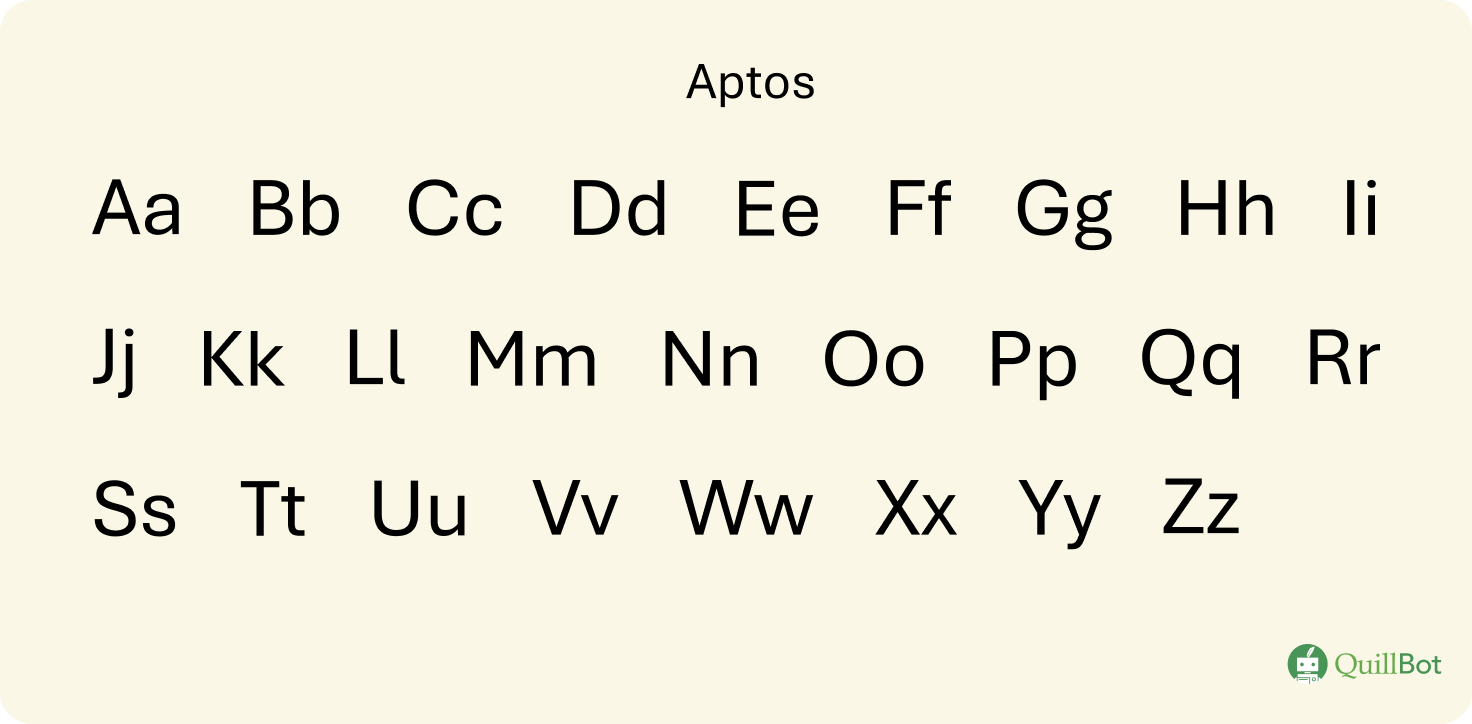
Aptos | La nouvelle police qui monte
Avril 2021, un petit séisme secoue la planète 2.0 : Microsoft annonce le prochain remplacement de Calibri, qui tenait le haut du pavé depuis bientôt 15 ans, en tant que police par défaut des logiciels de la suite Microsoft Office.
À cette époque, cinq polices d’écriture entrent en lice : Bierstadt, Grandview, Seafond, Skeena et Tenorite.
Cependant, c’est un tout autre nom qui s’imposera finalement en 2023.
Aptos, absente de la liste initiale, vraiment ? …
- Année de création : 2021
- Pays de création : États-Unis
- Créateurs : Steve Matteson
- Type d’empattement : Sans empattement (sans serif)
- Classification VoxAtypi : Linéale néo-grotesque
- Popularité : ++ (très utilisée depuis sa sortie car présente par défaut sur Windows, appréciée pour le vent de modernité qu’elle apporte sans sombrer dans trop de fantaisie)
- Image véhiculée : Nette, sérieuse, moderne et classique à la fois
- Point d’attention particulier :
- A succédé à Calibri comme police par défaut configurée sur les applications de la suite Microsoft Office.
En vérité, Aptos se trouvait bien dans la liste des prétendantes au trône Office… mais sous un autre nom.
Un trône ô combien convoité, sinon le Graal ultime pour une police d’écriture née dans les années 2000, et pour cause : en raflant la mise, Aptos est passée, en un temps infime, de l’anonymat à l’une des fonts les plus utilisées au monde.
Police Aptos : histoire et développement
Après 15 ans de bons et loyaux services pour les utilisateurs des applications de la suite Microsoft Office (Word, Excel, PowerPoint, Outlook, etc.), les instances dirigeantes et les développeurs de Microsoft décident qu’il est temps d’offrir à Calibri, paramétrée comme police par défaut depuis 2007, une retraite bien méritée.
Pour ce faire, il leur faut nommer une remplaçante. Le cahier des charges est simple à première vue : l’heureuse élue devra reprendre toutes les qualités pratiques et esthétiques qui ont fait la gloire de Calibri, tout en insufflant un vent de modernité et d’innovation à ses logiciels phares.
Qu’à cela ne tienne, cinq polices retiennent l’attention des équipes et font l’objet d’une présélection communiquée à la presse en avril 2021 :
- Bierstadt,
- Grandview,
- Seafond,
- Skeena,
- et Tenorite.
Les jeux de caractères sont mis à disposition des utilisateurs, afin de récolter leurs premières impressions et de sonder leurs préférences.
Deux ans plus tard, les délibérations ont lieu et le verdict tombe : la grande gagnante n’est autre que Bierstadt, qui a changé de nom entretemps.
À l’été 2023, on annonce pour les prochains mois le déploiement progressif d’Aptos.
Jugé trop complexe à prononcer, trop peu anglo-saxon dans ses sonorités et manquant de rondeur, ce nom est finalement abandonné au profit d’Aptos, qui là encore ne découle pas d’un enchaînement de syllabes hasardeux.
Aptos est le nom d’un census-designated place californien, soit littéralement un « lieu désigné par le recensement » une sorte de communauté type où l’on pratique des enquêtes statistiques. Les résultats desdites enquêtes sont censés être représentatifs des communes états-uniennes de taille et de morphologie similaires.
Aptos, une police à la fois moderne et classique
Tout comme l’était déjà Calibri, Aptos est une police linéale, ou sans empattement.
La morphologie de ses caractères emprunte aux typographies suisses, à l’image d’Helvetica, qui s’en inspire très largement.
Ce type de police s’oppose aux polices dites avec empattement, une distinction que l’on opère selon un critère visuel immédiatement reconnaissable.
- Les polices serif (avec empattement en français) possèdent de petits « pieds », crochets ou traits décoratifs aux extrémités de leurs caractères.
Elles évoquent immédiatement un design classique, sérieux, et confèrent à la communication un caractère institutionnel symbolique d’une certaine autorité.
Elles sont aussi très utilisées dans l’édition et la presse écrite, car jugées plus adaptées à la lecture de textes sur le long court.
Exemples de polices avec empattement : Baskerville, Garamond, Palatino Linotype, Times New Roman… - À l’inverse, les polices sans serif ne possèdent pas d’empattements. Leurs lignes sont droites et nettes.
Leur aspect est moderne et minimaliste ; leur design épuré, mais accessible.
On les utilise volontiers sur le web en raison de leur lisibilité optimisée pour les écrans et de leur côté « percutant ».
Car c’est aussi la force de ces polices pensées pour un usage de masse, et auxquelles ont été consacrés des budgets conséquents : il n’y a pas de mauvaise surprise lorsqu’il s’agit de les passer en gras ou en italique.